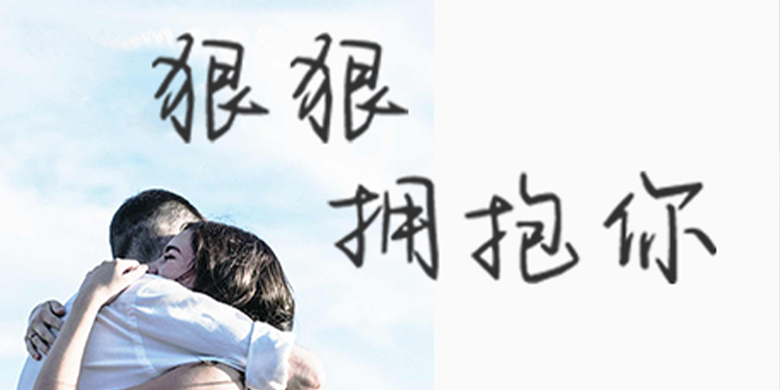
方正手迹-狠狠拥抱你
字体品牌: 方正手迹 设计师:刘晔 字体分类:创意书写 字体属性:精品字 字符集:大陆简体(GB2312-80) 发布时间: 2020
狠狠拥抱你是一款随性感觉的手写体。该字体整体大小不一,错落有致有一种书法书写的韵律感。笔画洒脱转折果断,干净利落。该字体适用于文艺类的书刊、品牌广告和产品包装设计,以及社交网络的个性化用字。